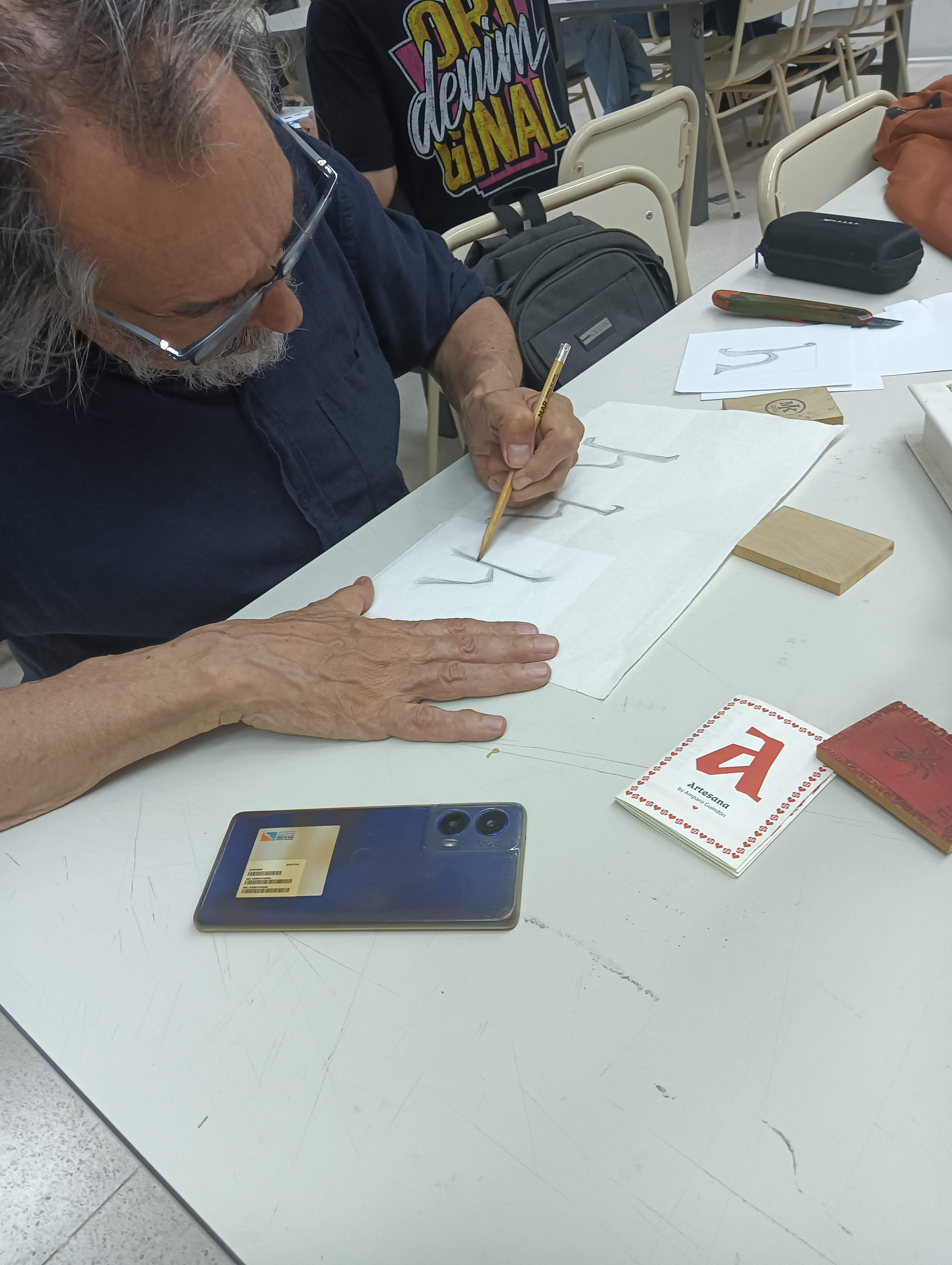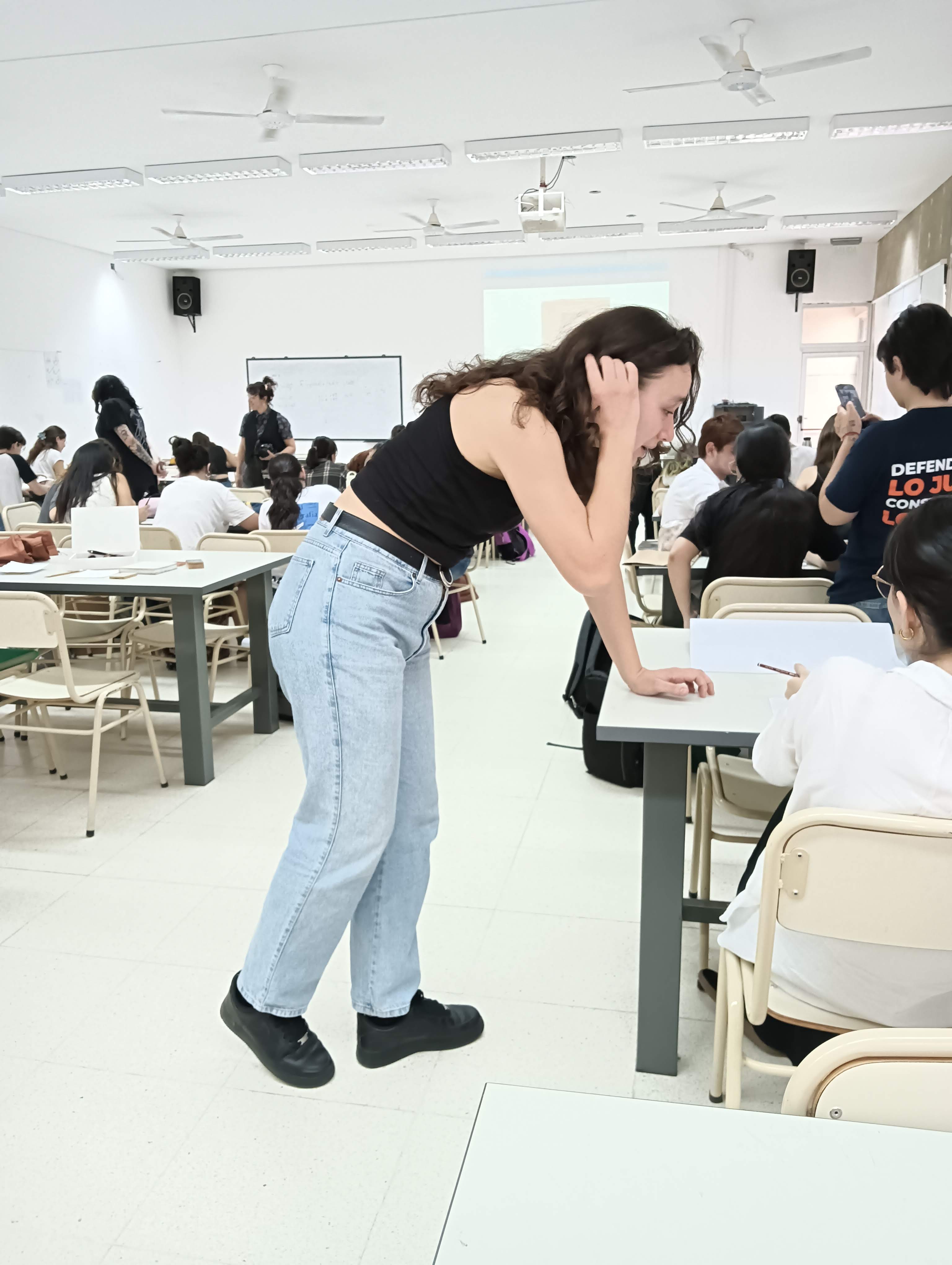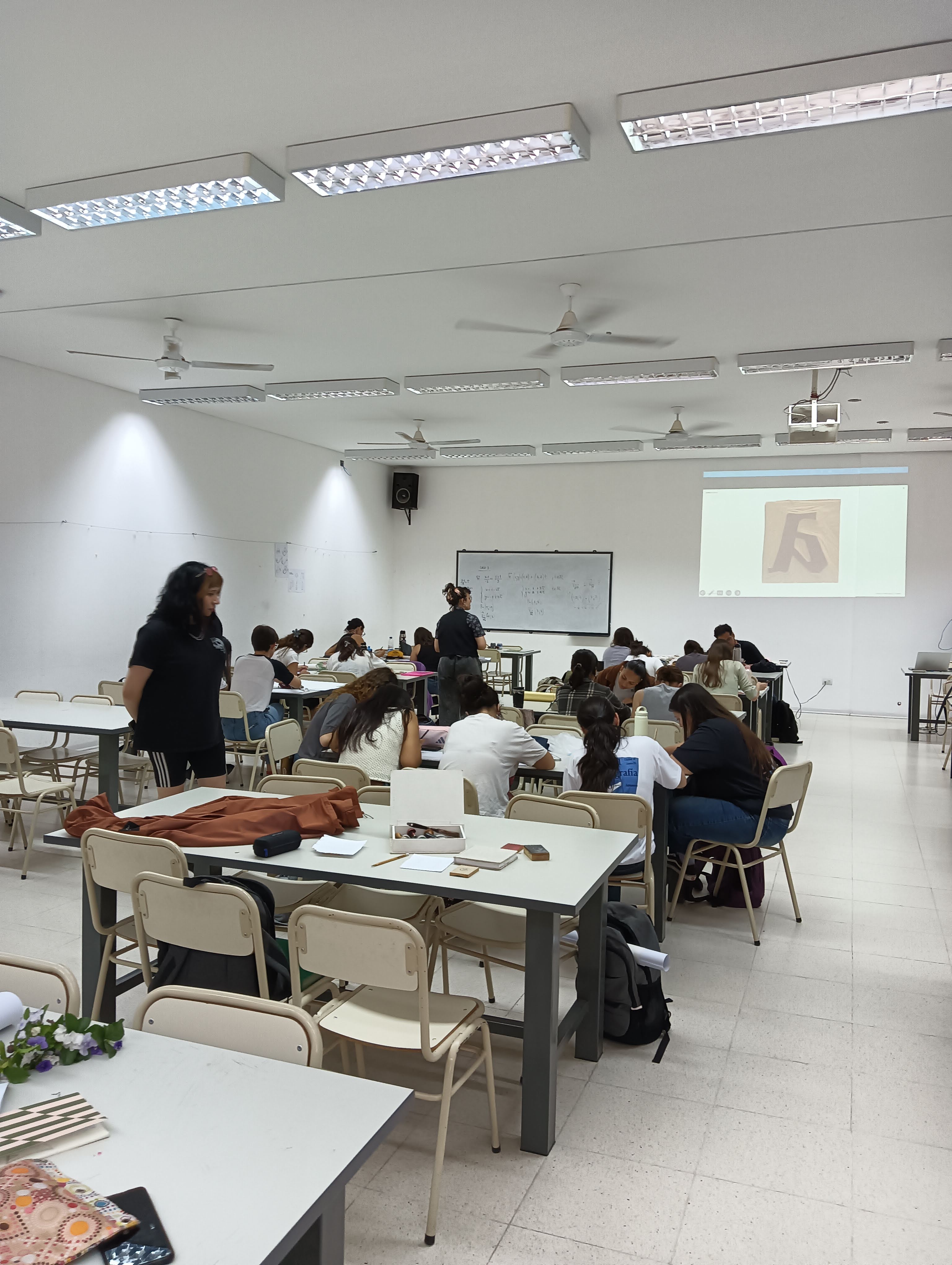
Charla tipografía Artesana + Taller de Grabado tipográfico. Amparo Guindón
LETRAS GRABADAS
Búsqueda morfológica de letras a través de un ensayo xilográfico.
Este taller propone un ejercicio morfológico y tipográfico a través de una práctica 100% analógica que combina dibujo, grabado en madera e impresión artesanal. Un reencuentro con los oficios manuales, ideando letras con gubias en las manos.
Paralelamente se ofreció una charla sobre la tipografía Artesana, desarrollada por la misma profesional, como introducción al tema.